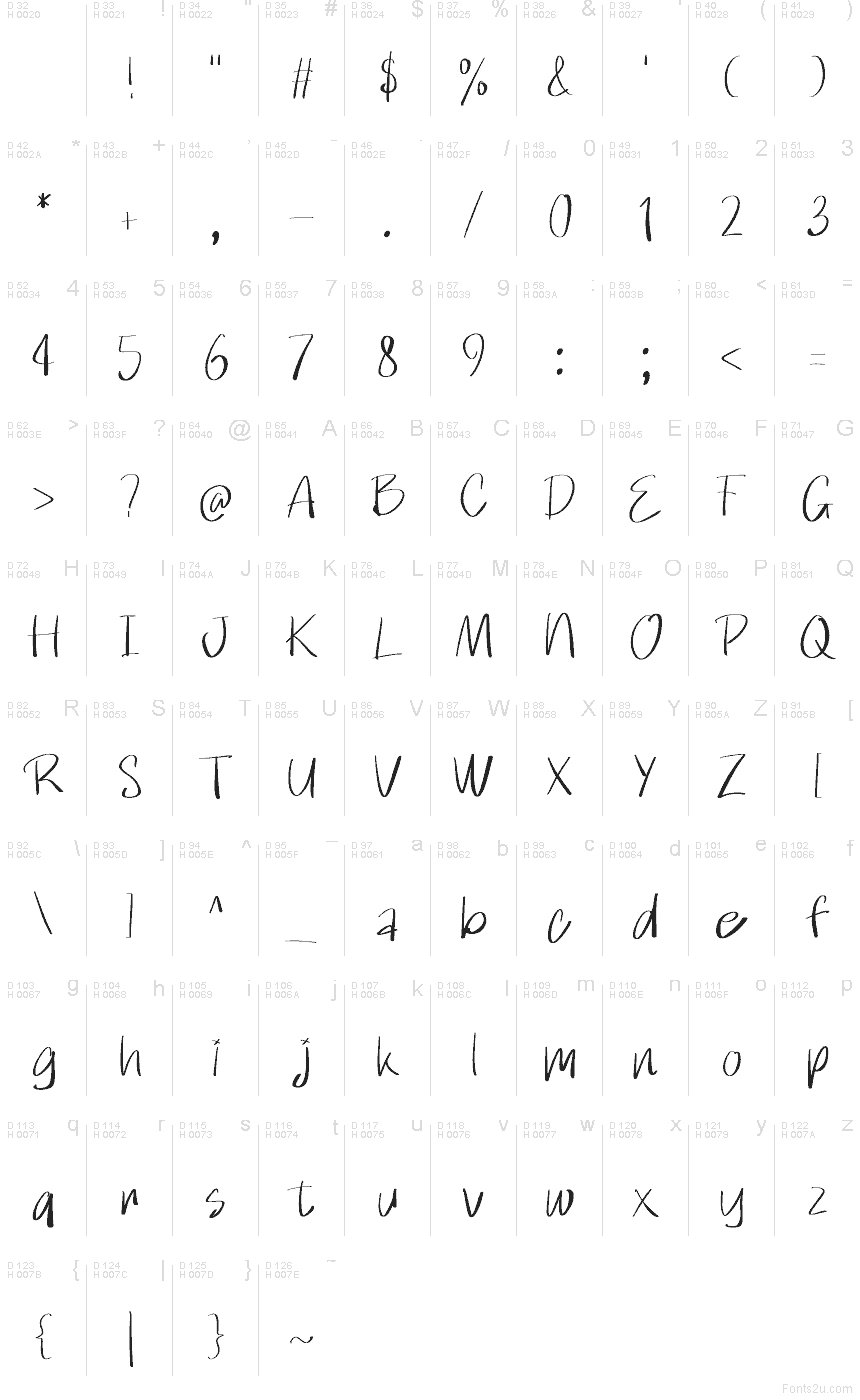
Broken Junior
La police Broken Junior du studio Hello Good Studio est une écriture manuscrite gratuite, caractérisée par des traits lâches et irréguliers qui lui confèrent un rythme rapide et décontracté. Les lettres conservent une forme calligraphique haute et ouverte, tandis que leurs contours légèrement rugueux et leurs jointures étroites donnent à l'ensemble un aspect dessiné à la main, subtilement imparfait.
Broken Junior est une police gratuite idéale pour les logos, les citations sur affiches, le packaging, les visuels pour réseaux sociaux ou encore de courts textes d'invitation, lorsque vous recherchez une esthétique informelle mais structurée. Sa structure manuscrite apporte une touche personnelle et esquissée, tout en conservant une excellente lisibilité à chaque mot.